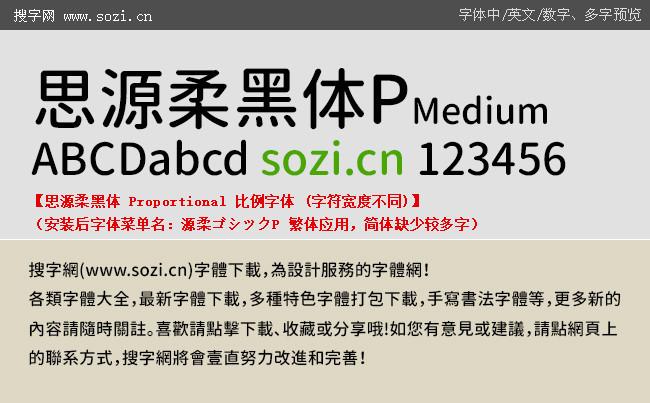
思源柔黑P-Medium
搜字網(wǎng)給大家提供一款思源柔黑P-Medium中文字體下載,思源柔黑體由思源黑體改造而來,由日本作者自家製フォント工房制作,所以部分簡體中文可能會(huì)不顯示,柔黑承襲了「思源黑體」原有的優(yōu)雅,在文字邊角以圓邊進(jìn)行處理,相比原來思源黑體更加柔和,似黑似圓,介于二者之間,而P系列為字符寬度不同的柔黑體系列。適用于排版設(shè)計(jì)、包裝設(shè)計(jì)、海報(bào)設(shè)計(jì)等應(yīng)用。